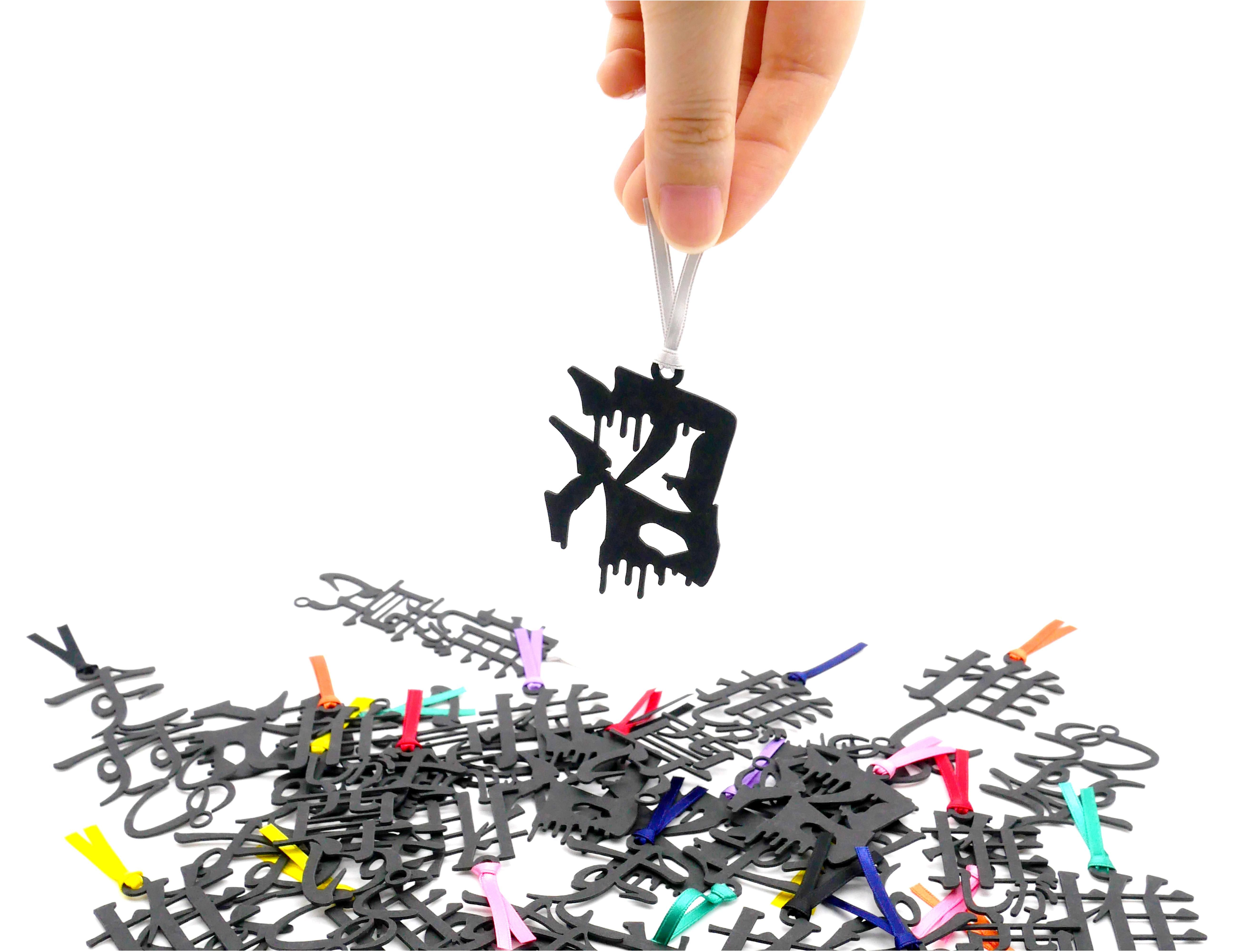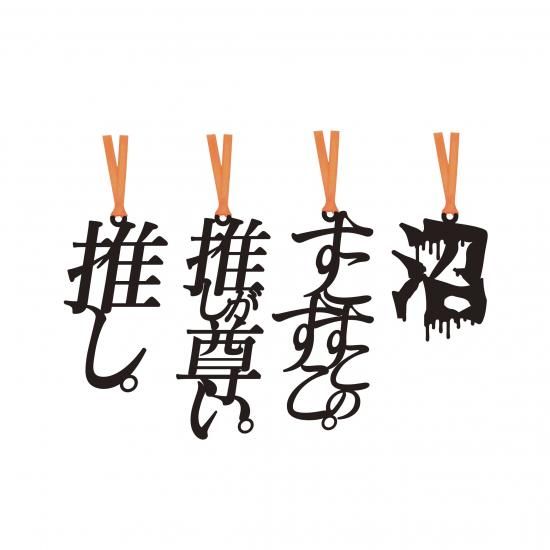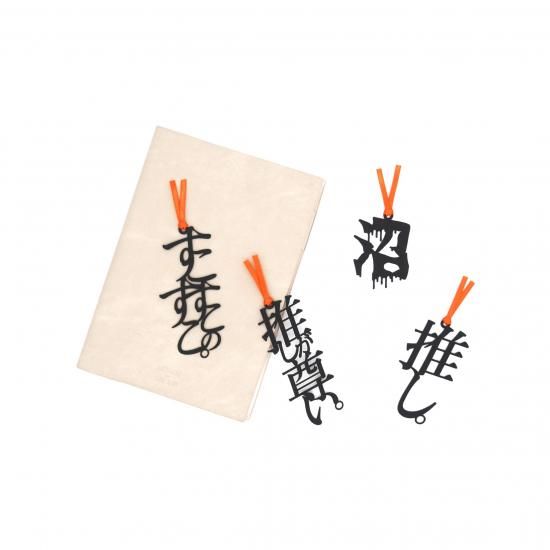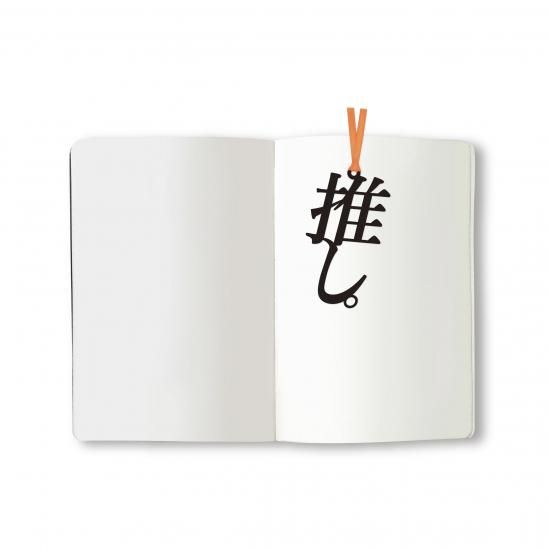
文字の推しのしおり【オレンジ4種】推しのすべてを受け入れたいセット
文字の推しのしおり『推し。』
推しそのものをしおりにしてみました。
なぜ推すのか?そこに推しがいるから。
推しと決めたら、とにかく推すべし。推しは推す!
文字の推しのしおり『推しが尊い。』
推しの尊さをしおりにしてみました。
なんでこんなに尊いのだろう。
過ぎる尊さに無限の敬意と感謝を込めて。
文字の推しのしおり『すこすこのすこ』
推しへの溢れる愛をしおりにしました。
すこすこすこすこ
文字の推しのしおり『沼』
沼そのものをしおりにしてみました。
ここは沼なのか。はたまた楽園か。
どっぷり浸かると毎日が楽しくて仕方がない。
木材パルプや綿を原料とした環境素材を採用し、耐久性・耐水性に優れたファイバーの特徴を活かすことで、言葉がフォントごと切り取られたような巧緻で美しい『文字のしおり』のデザインが実現しています。